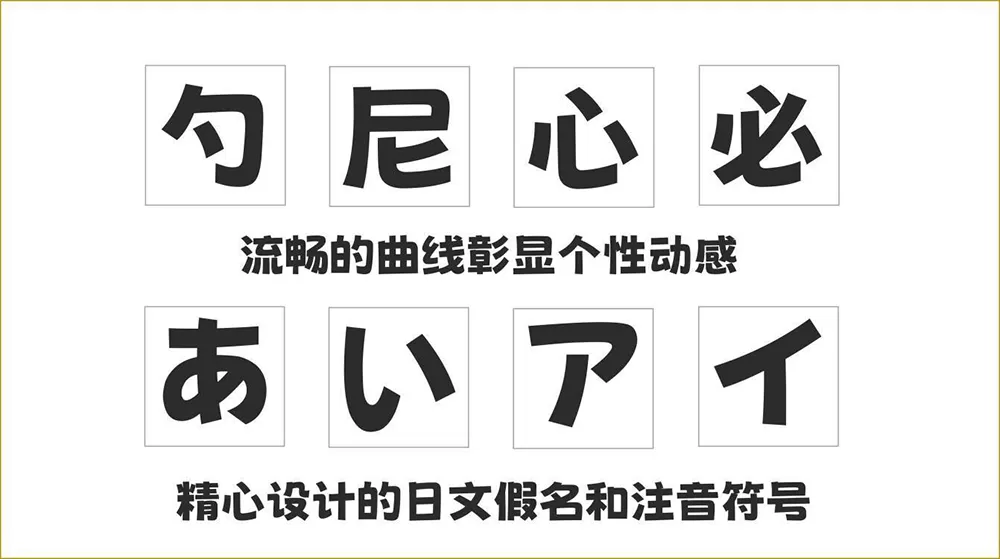
字体介绍
当下市面上的免费商用中文字体,大多集中在综艺体这类美术字体范畴。兼具萌趣气质与实用属性的卡通标题字体,选择面十分狭窄,多数情况下需要付费采购。为了填补这一市场缺口,荆南字坊将筹备多时的「波波黑」字体,正式开放免费商用权限。
这款字体在 2023 年 3 月 9 日更新至 1.70 版本,不仅补全了方正简繁、日文 STD 字库以及部分香港地区的常用汉字,还根据实际使用需求增补了若干异体字。目前字体共收录 15905 个字符,全面覆盖 GB2312 编码标准,足以满足日常各类设计场景的使用需求。
荆南波波黑的笔画设计极具辨识度:横竖笔画并非规整的直线形态,而是带有自然的波浪起伏感,整体观感俏皮灵动,满溢着童真趣味。
荆南波波黑字体展示样例一 荆南波波黑字体展示样例二
设计亮点:
• “口”字左上角出头处理,根据字形灵活调整;
• 日文假名与注音符号经过精心设计;
• 流畅的曲线赋予字体个性与动感。